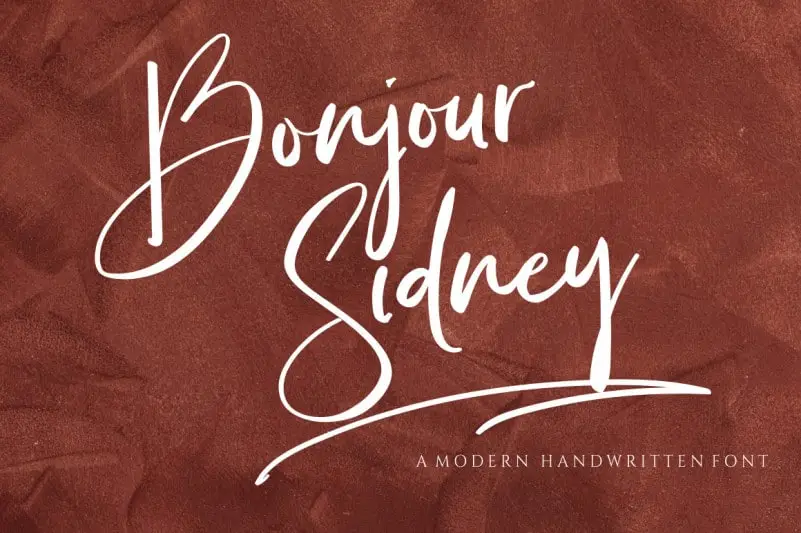
Bonjour Sidney Calligraphy Font – Fonte Grátis
Bonjour Sidney Calligraphy Font
A fonte ‘Bonjour Sidney Calligraphy Font’ traz uma estética moderna e feminina que se destaca entre as outras tipografias. Seu design elegante combina elementos que remetem à sofisticação do século XXI, proporcionando um toque atraente para logotipos, materiais de marca, embalagens de eventos, sobrepostas nas mídias sociais e cartões de felicitações. Este é um recurso gráfico ideal para aqueles que desejam dar um ar sofisticado aos seus trabalhos visuais sem perder a delicadeza necessária para projetos como festas, casamentos ou mensagens pessoais. Com ‘Bonjour Sidney Calligraphy Font’, suas criações ganham um brilho especial e uma personalidade única, tornando-se elementos distintivos que refletem seu estilo único.